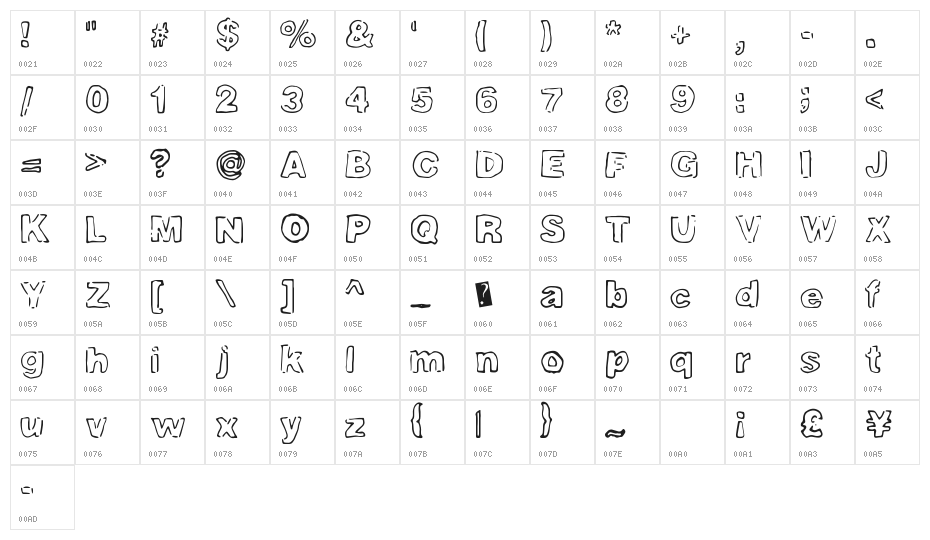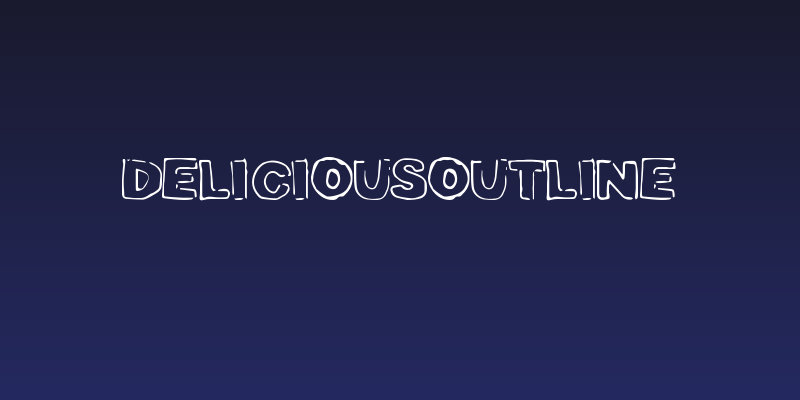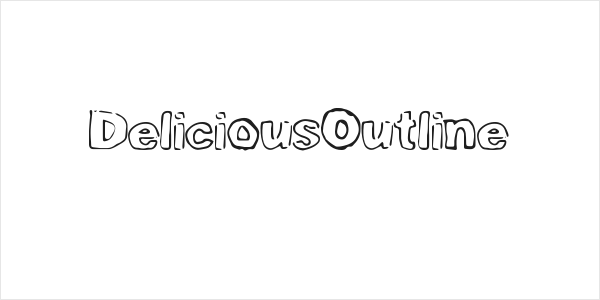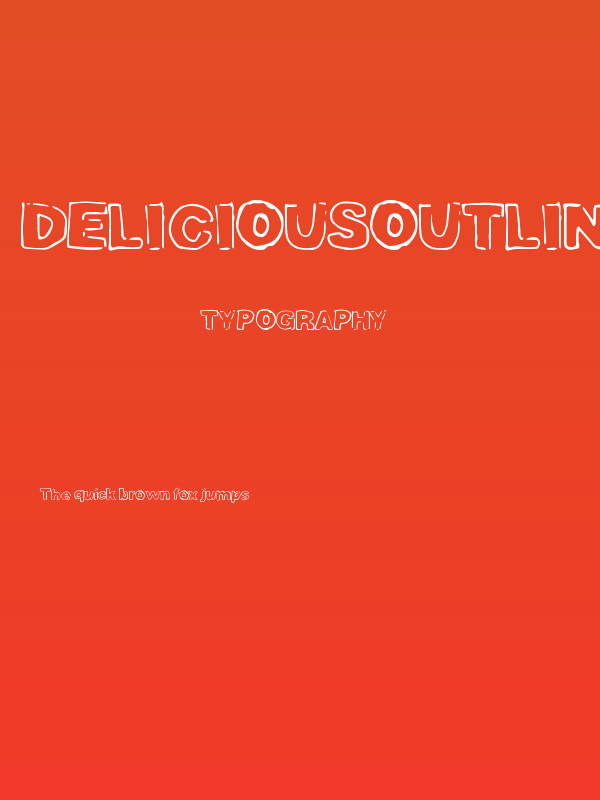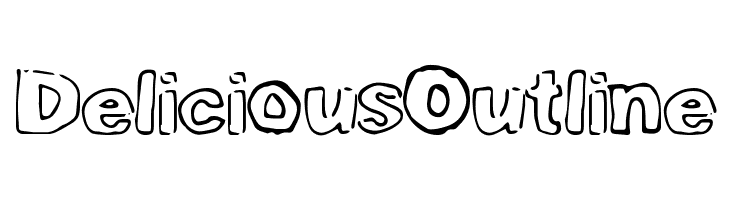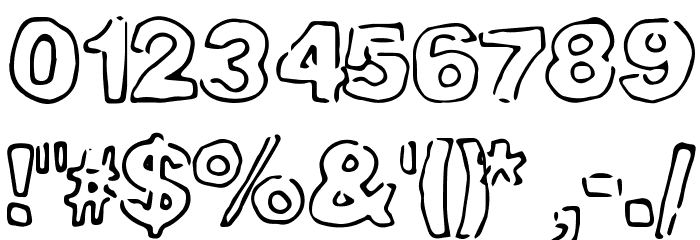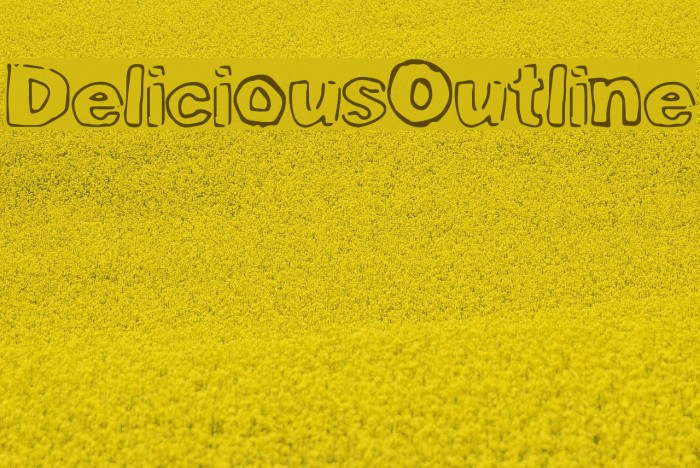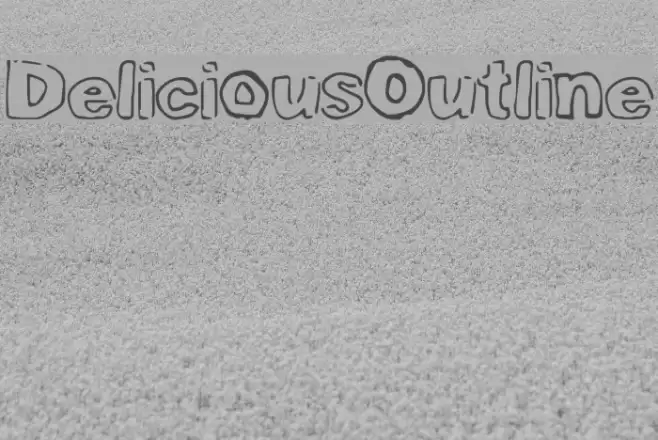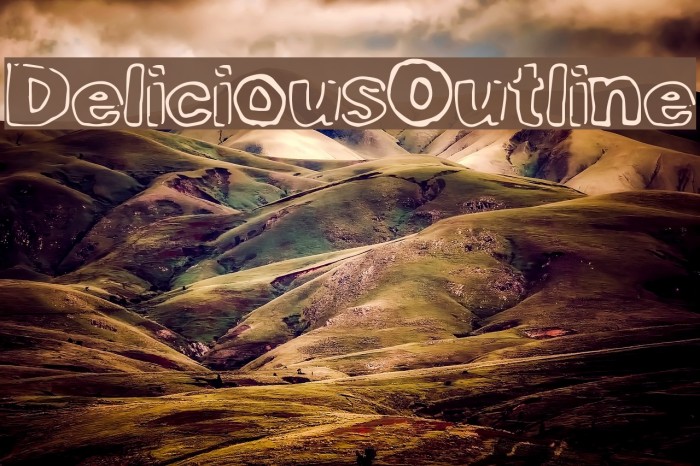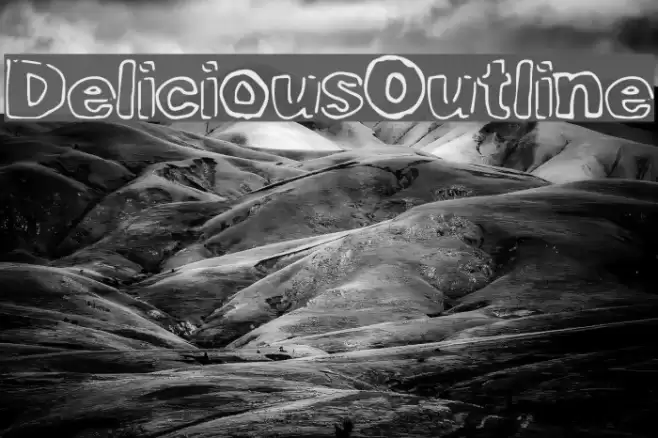
DeliciousOutline Font
| Style général | Playful, Whimsical, Modern |
| Projets proposés | Ideal for children's book covers, playful posters, greeting cards, and creative branding projects. |